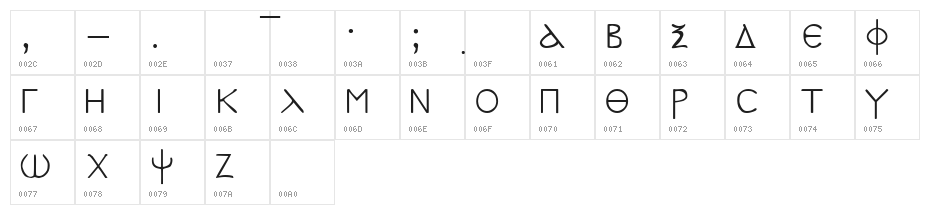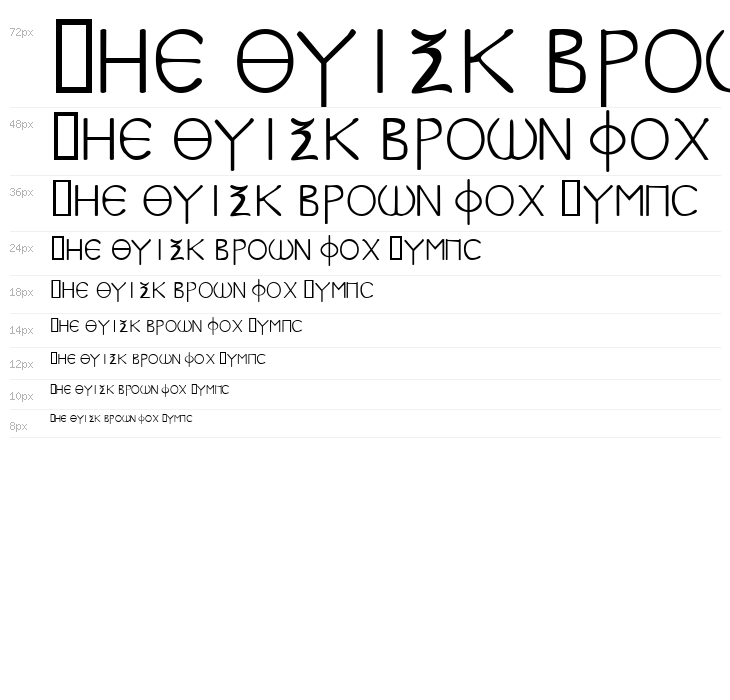
SPDoric Font
| Progetti proposti | Ideal for historical or educational publications, branding for classical-themed products, or artistic projects that require a touch of antiquity. |